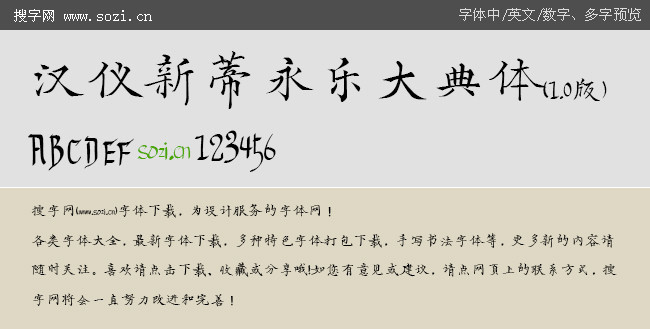
漢儀新蒂永樂(lè)大典體1.0
搜字網(wǎng)提供一款漢儀新蒂永樂(lè)大典體1.0字體下載,漢儀新蒂永樂(lè)大典體是根據(jù)我國(guó)著名文獻(xiàn)永樂(lè)大典定制而出的字體,由漢儀新蒂工作室出品,漢儀新蒂工作室成立于2016年,由漢儀字庫(kù)與新蒂字體聯(lián)合成立,本字體獨(dú)具特色的筆鋒讓字體看起來(lái)更加的蒼勁有力流暢大方,適合應(yīng)用于海報(bào)設(shè)計(jì)、書(shū)籍排版、包裝設(shè)計(jì)等應(yīng)用。(本字體為個(gè)人非商用版,如需要商用請(qǐng)聯(lián)系漢儀公司購(gòu)買(mǎi)版權(quán))